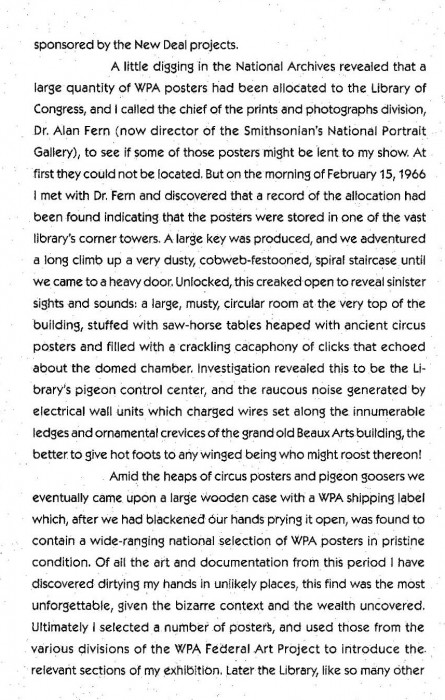
[Mitglied insk…] Geschrieben Mai 24, 2015 Teilen Geschrieben Mai 24, 2015 wertes Forum, habe in einem US-amerikanischen Katalog eine Schrift entdeckt, die mir auf Anhieb sofort gut gefallen hat. Könnt Ihr mir den Schrifttyp nennen und mich anhand des Beispiels auch darüber aufklären wie groß die Schrift ist und wieviel Zeilenabstand hier gewählt wurde. Herzlichen Dank im Voraus Ulrich Link zu diesem Kommentar
[Mitglied catf…] Geschrieben Mai 24, 2015 Teilen Geschrieben Mai 24, 2015 Wie bitte sollte man erkennen, welche Schriftgröße das ist, wenn man die Abmessung des Satzspiegels nicht kennt? Link zu diesem Kommentar
Beste Antwort [Mitglied eb3b…] Geschrieben Mai 24, 2015 Beste Antwort Teilen Geschrieben Mai 24, 2015 Das ist auf jeden Fall eine Kabel. Wie groß die ist kann man wirklich nicht sagen und den Durchschuss noch weniger … Link zu diesem Kommentar
[Mitglied Vitr…] Geschrieben Mai 24, 2015 Teilen Geschrieben Mai 24, 2015 Bei der Schriftart dürfte es sich um die Kabel von Rudolf Koch handeln. Allerdings wohl um die Version welche von einem Victor Caruso 1976 für ITC verändert wurde. Mir gefällt das Kochsche Original aber sehr viel besser, die veränderte Schrift ist aber ev. etwas besser lesbar. Link zu diesem Kommentar
[Mitglied Pach…] Geschrieben Mai 24, 2015 Teilen Geschrieben Mai 24, 2015 Ich hoffe, Du denkst nicht darüber nach, die für Dein Buch zu verwenden. Als Textschrift ist sie denkbar ungeeignet. Link zu diesem Kommentar
[Mitglied insk…] Geschrieben Mai 24, 2015 Themen-Ersteller Teilen Geschrieben Mai 24, 2015 Herzlichen Dank! Das ging ja schnell. Die Schrift wird in einem Plakatkatalog verwendet. Für ein ähnliches Projekt würde auch ich gerne Kochs Kabel verwenden. Gruß und Dank an die Problemlöser Ulrich Link zu diesem Kommentar